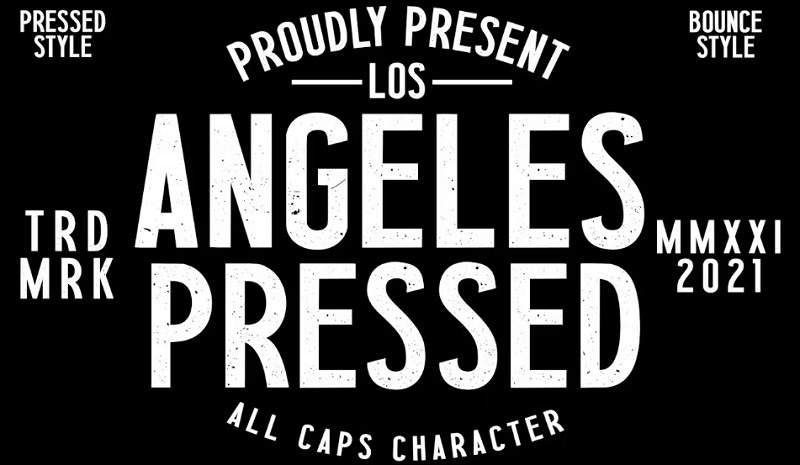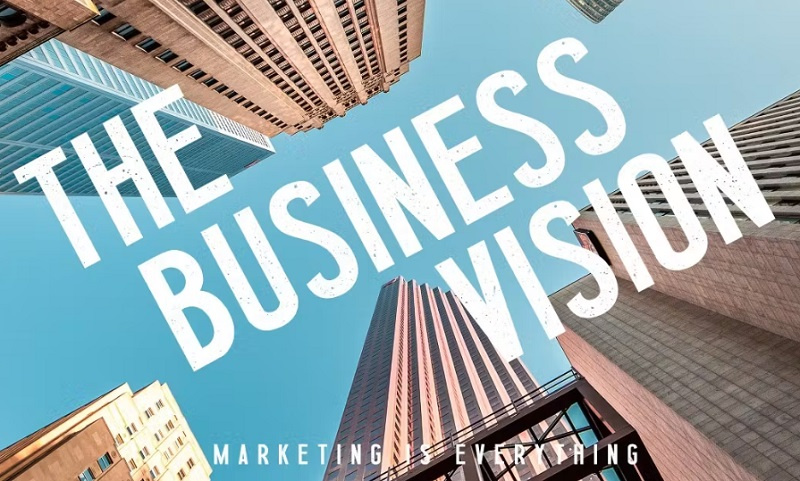
فونت انگلیسی روزنامه از جی اف ایکس دانلود. این مجموعه شامل 2 فونت روزنامه مناسب برای استفاده در طراحی ها، وب و ... می باشد. همچنین این فونت روزنامه انگلیسی برای محصولات خلاقانه دیجیتال، چاپی، پوسترها، پست های رسانه های اجتماعی، برندسازی، پروژه های شخصی و غیره مناسب است. این فونت با فرمت های OTF - WOFF - TTF ارائه شده است.
1- فونت روزنامه انگلیسی Los Angeles Press
Los Angeles Press یک فونت انگلیسی روزنامه و مجله است که دارای کاراکترهای گستردهای می باشد. مناسب برای لوگوها، برندسازی، طراحی بستهبندی و موارد دیگر. برای دانلود فونت انگلیسی و مشاهده پیش نمایش آن در ادامه با ما همراه باشید.